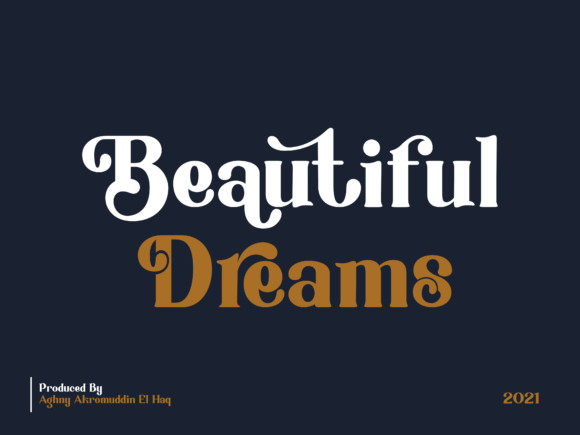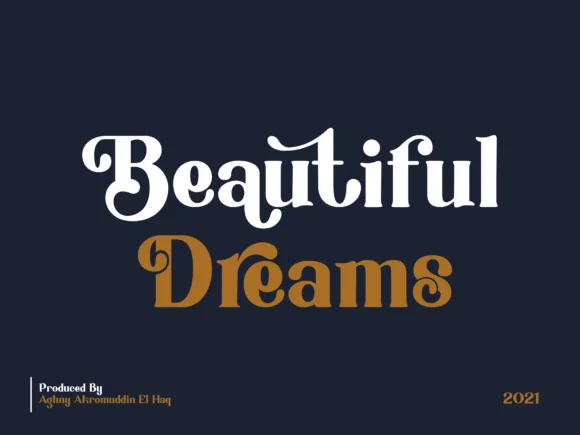
Название: Abimanue Font (2021)
Abimanue - это классный и аутентичный шрифт.
Влюбитесь в его невероятно универсальный стиль и используйте его для создания эффектных дизайнов!